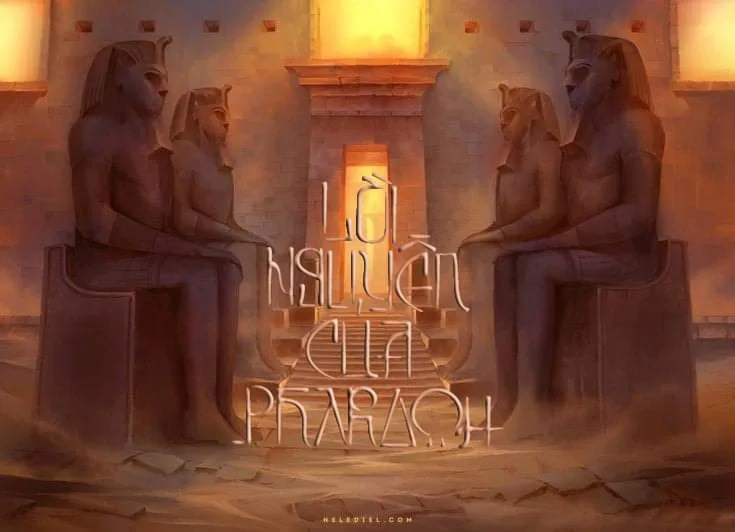
Font Việt hóa Architype mang phong cách đậm chất cổ xưa phù hợp làm font triện và thiết kế các sản phẩm hơi hướng xưa.
Giới thiệu Font Việt hóa Architype AD 2014
Với cách nhìn về con chữ khá đặc biệt, nhà thiết kế đã cho ra mắt bộ font này với mốc thời gian được ấn định là 2014. Điều này còn là một huyền bí về mặt nào đó bạn hãy cùng tìm hiểu xem nhé.
1. Architype Phù hợp làm Font Triện
Nhà thiết kế: Bogdan Balatchi đã tạo ra một bộ font độc đáo mang phong cách riêng của ông ấy. Font được phát hành và bán trên myfont vào năm 2014. Với sự đón nhận của cộng đồng năm 2020 nhà phát hành đã sửa lỗi và cập nhật thêm nhiều glyph hơn.
2. Nguồn gốc, cảm hứng thiết kế và ứng dụng phông chữ miễn phí
Font được lấy cảm hứng từ thư pháp Slavonic cổ xưa, được hoàn thiện với giao diện hiện đại, mới mẻ và đầy ngẫu hứng.
Architype AD-2014 là một font chữ được thiết kế mang âm hưởng lịch sử, có màu sắc tôn giáo đặc trưng. Là 1 bộ font độc đáo đáng có trong bộ sưu tập FONT VIỆT HÓA của bạn để phục vụ cho việc design.
Những sự thay đổi sau khi việt hóa
Nhận thấy sự đặc biệt của font và sau đợt vote khá sôi nổi từ các thành viên của FontZin, FzTeam đã Việt hóa font này đồng thời tinh chỉnh một số để phù hợp với Tiếng Việt hơn.
- Căn chỉnh một số metrics của glyph để font auto type có kerning chuẩn hơn. (font không có kerning bằng code mà bằng metrics)
- Chỉnh sửa một số ký tự A O Q U Y S T W… để hoàn thiện hơn, phù hợp với font triện hơn.
- Chuyển ký tự thường thành outline.
- Và một số thay đổi nhỏ trong font chờ bạn trải nghiệm 🙂